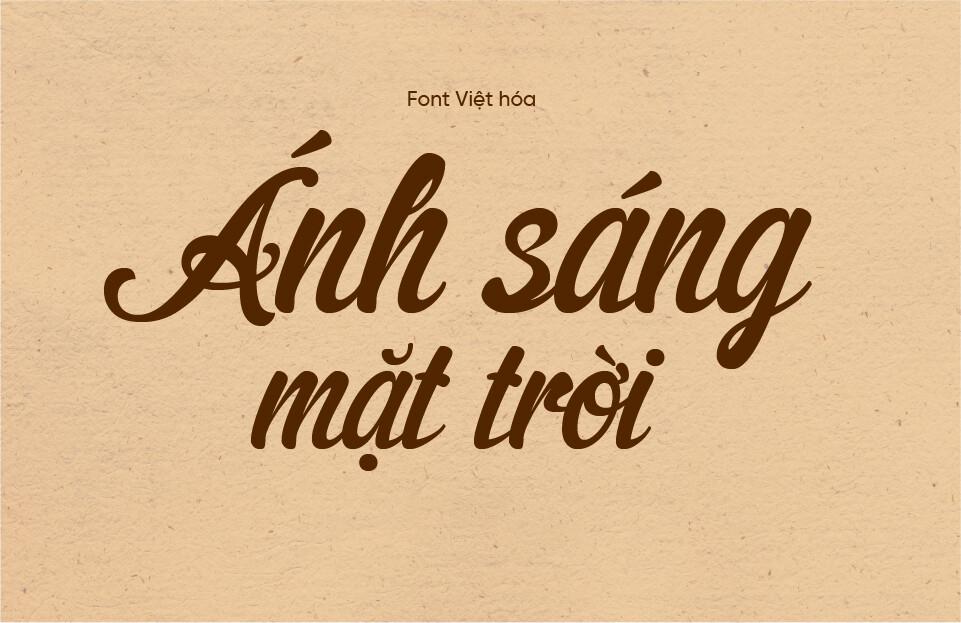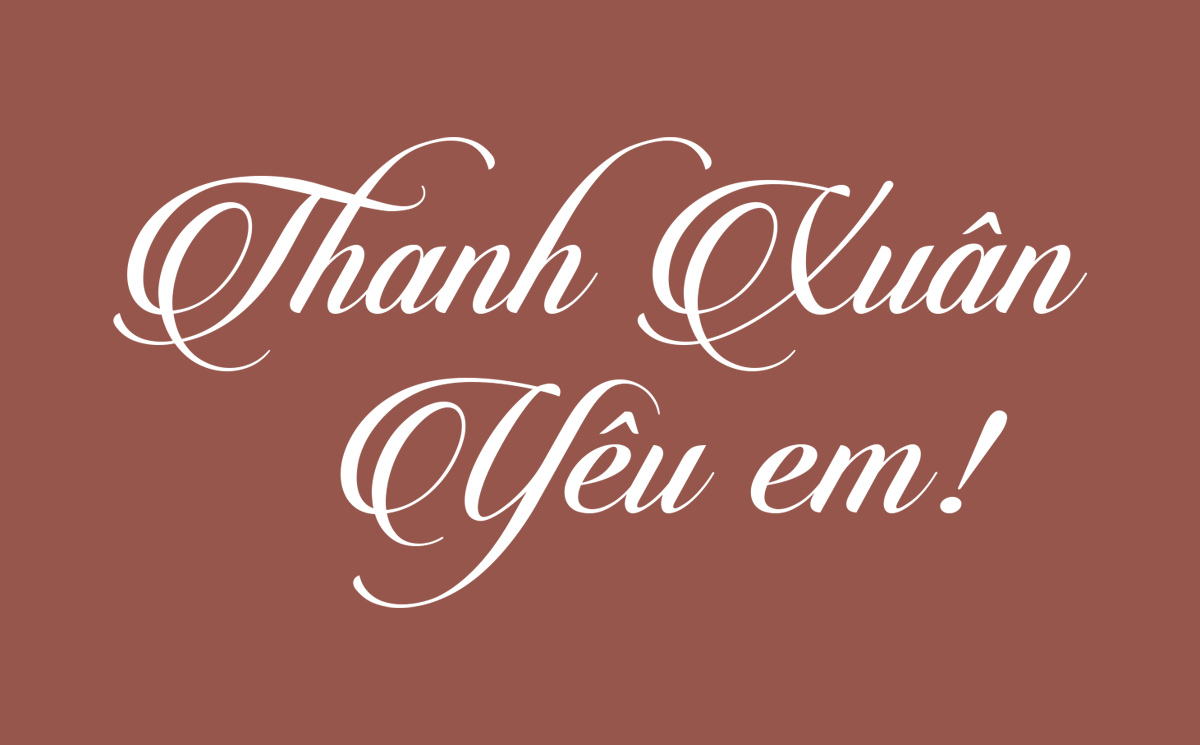
Bộ Font UVF là gì? Tầm ảnh hưởng trong cộng đồng thiết kế Việt Nam
Cùng với các hệ font danh tiếng như SVN hay VNF, UVF đóng vai trò như một kho tài nguyên chuẩn mực, giúp nâng tầm diện mạo đồ họa chữ viết tiếng Việt trên các ấn phẩm thương mại.
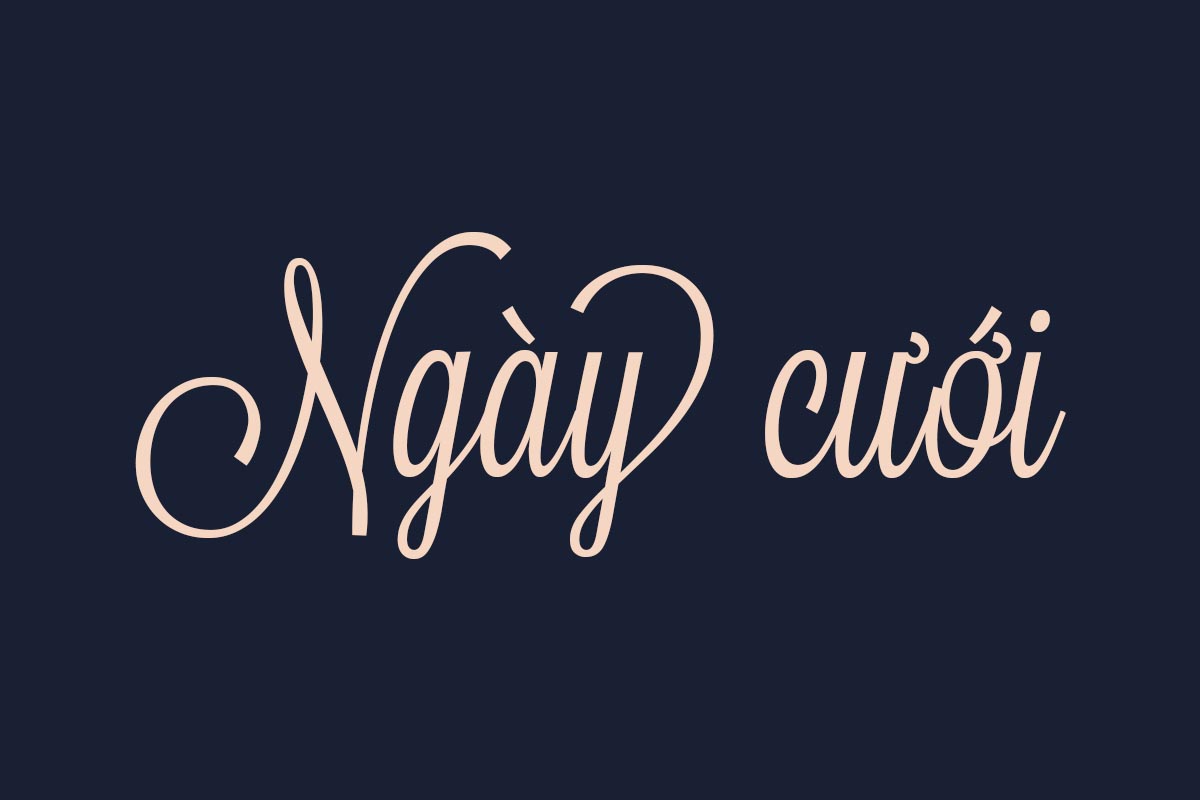
Nguồn gốc và tiêu chuẩn Việt hóa chất lượng cao
Đặc trưng lớn nhất của Font UVF là tính chọn lọc khắt khe. Các phông chữ được gắn tiền tố UVF đều có xuất xứ từ những xưởng đúc chữ hàng đầu thế giới, sở hữu cấu trúc hình học chuẩn xác, tính thẩm mỹ vượt trội và khả năng ứng dụng thực tế cao. Thay vì phải đối mặt với các bản font lỗi thời, việc sử dụng hệ thống UVF giúp các nhà thiết kế tiếp cận được những xu hướng Typography quốc tế mới nhất nhưng vẫn đảm bảo tính tương thích hoàn hảo với ngôn ngữ mẹ đẻ.
Kỹ thuật xử lý dấu câu tiếng Việt chuẩn xác và hài hòa
Nỗi đau muôn thuở của designer là khi tìm được font chữ đẹp nhưng bộ dấu tiếng Việt lại bị thô kệch, lệch vị trí hoặc làm gãy nhịp điệu của dòng văn bản. Khi bạn tải trọn bộ Font UVF tiếng Việt, toàn bộ các dấu thanh (sắc, huyền, hỏi, ngã, nặng) cùng các ký tự có mũ (ă, â, đ, ê, ô, ơ, ư) đều đã được các chuyên gia vẽ tay lại tỉ mỉ. Từng dấu câu được cân chỉnh chuẩn xác về độ dày, độ mở và khoảng cách, đảm bảo tiêu đề trên bao bì luôn toát lên vẻ chỉn chu, thoáng đãng và đẳng cấp.
Các phong cách nổi bật trong bộ sưu tập font UVF
Khi thực hiện tải trọn bộ Font UVF, bạn sẽ sở hữu một hệ sinh thái biến thể phong phú đáp ứng mọi cấp độ phân cấp thông tin (Typography Hierarchy) trên bản vẽ bao bì:
- Nhóm UVF Sans-serif hiện đại: Tiêu biểu với các cấu trúc hình học tối giản, dứt khoát, là giải pháp hoàn hảo cho bảng thành phần, mã vạch, thông số kỹ thuật hoặc các thương hiệu mang hơi thở công nghệ tân thời.
- Nhóm UVF Serif sang trọng: Sở hữu chân chữ sắc sảo, độ tương phản nét thanh đậm tinh tế, cực kỳ phù hợp cho tiêu đề hộp quà tặng doanh nghiệp, vỏ hộp nước hoa và mỹ phẩm cao cấp.
- Nhóm UVF Script & Handwriting: Những đường nét uốn lượn bay bổng, mềm mại như chữ ký cá nhân, lý tưởng cho thiệp mời sự kiện, thư cảm ơn đính kèm hoặc các sản phẩm thủ công tinh tế.
- Nhóm UVF Display ấn tượng: Hình khối phá cách, độ dày nét lớn, giúp tên thương hiệu trên mặt chính của túi giấy hay nắp hộp thu hút trọn vẹn thị giác người xem ngay từ cái nhìn đầu tiên.
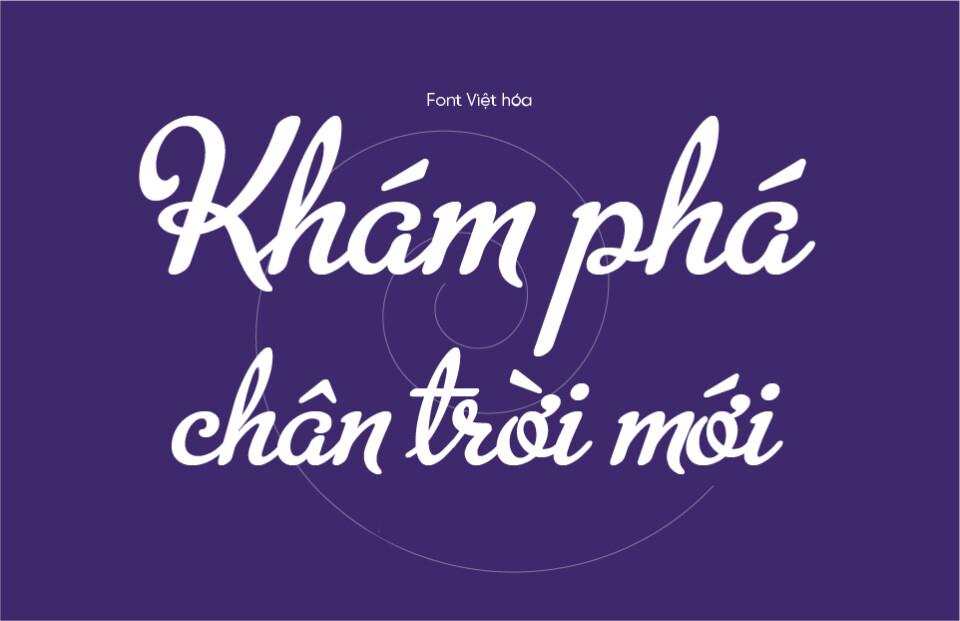
Tại sao designer nên tải trọn bộ Font UVF tiếng Việt cho thiết kế bao bì?
- Giữ vững tính đồng nhất cho toàn bộ hệ thống nhận diện: Việc sử dụng chung một hệ font UVF cho từ logo, bao bì, nhãn mác đến tài liệu truyền thông giúp thương hiệu xây dựng hình ảnh bài bản và chuyên nghiệp trong mắt khách hàng.
- Hạn chế tối đa rủi ro kỹ thuật tại xưởng in: Các bộ font UVF chuẩn kỹ thuật giúp file xuất in PDF gửi đến xưởng in Offset không bị lỗi biến dạng ký tự, bảo đảm thành phẩm ra đời chuẩn xác 100% như bản vẽ ban đầu.
| Nhóm Font | Định dạng file | Ứng dụng đề xuất tại Doozypack.vn |
| UVF Sans-serif | OTF, TTF | Bảng thành phần, hướng dẫn sử dụng, tem nhãn phụ. |
| UVF Serif | OTF, TTF | Hộp mỹ phẩm cao cấp, nhãn rượu vang, bao bì thời trang Luxury. |
| UVF Script & Display | OTF | Tiêu đề túi giấy, thiệp cảm ơn, bao bì bánh kẹo handmade. |
Lời khuyên từ xưởng in: Đối với các bản thiết kế in ấn bao bì cao cấp tại Doozypack.vn, bạn nên ưu tiên cài đặt định dạng OTF. Bản OTF giúp các đường cong của phông chữ giữ được độ mịn màng tuyệt đối khi xuất file PDF chất lượng cao, hạn chế tối đa tình trạng răng cưa khi phóng lớn tên thương hiệu.
Ứng dụng thực tế của font UVF trong sản xuất bao bì tại Doozypack.vn
Sự toàn diện của hệ thống font chữ UVF mang lại hiệu ứng thị giác đắt giá trên các dòng sản phẩm bao bì thực tế do Doozypack.vn sản xuất:
- Hộp giấy đựng Mỹ phẩm & Nước hoa: Nét chữ kiêu kỳ của các dòng UVF Serif kết hợp cùng kỹ thuật ép kim nhũ vàng tạo nên vẻ đẹp sang trọng, đẳng cấp chuẩn quốc tế cho vỏ hộp.